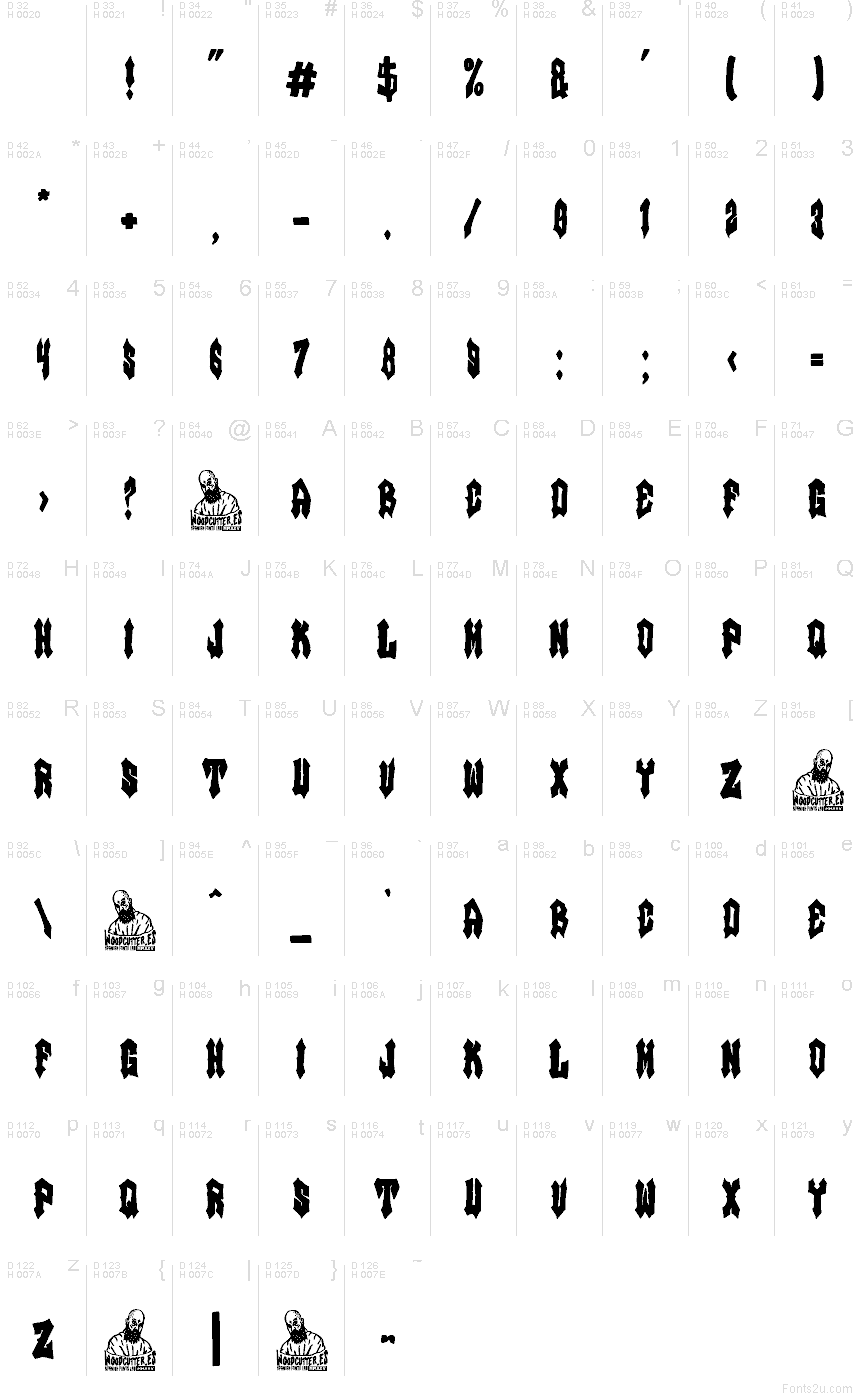
Talego Special
Talego Special je moderní gotické titulkové písmo od Woodcutter Manero, které přetváří styl blackletter v něco ostřejšího a grafičtějšího. Písmena působí jako vytesaná z drsných fazet – s hranatými zlomy, ostrými patkami a hustými siluetami, které dodávají verzálkám odvážný středověký náboj, aniž by sklouzávaly k přehnanému zdobení.
Skvěle se hodí na plakáty, obaly alb, herní tituly, grafiku na merch či branding pro bary nebo tetovací studia, kde bezplatné písmo potřebuje rychle vybudovat atmosféru. Použijte ho pro krátké titulky, názvy nebo monogramy, když chcete, aby drsný rytmus písmen vynikl a udržel kompaktní blok textu pohromadě.